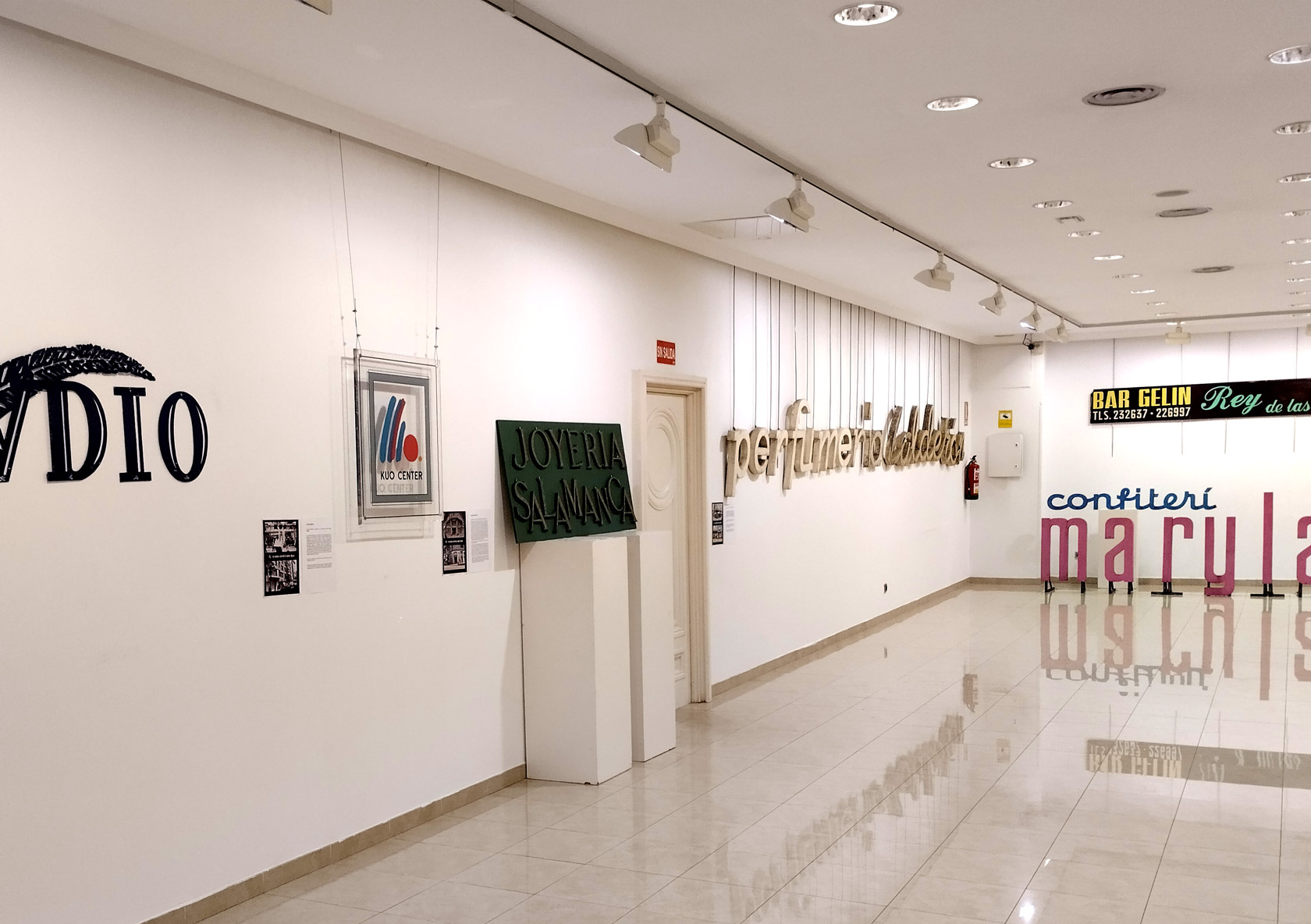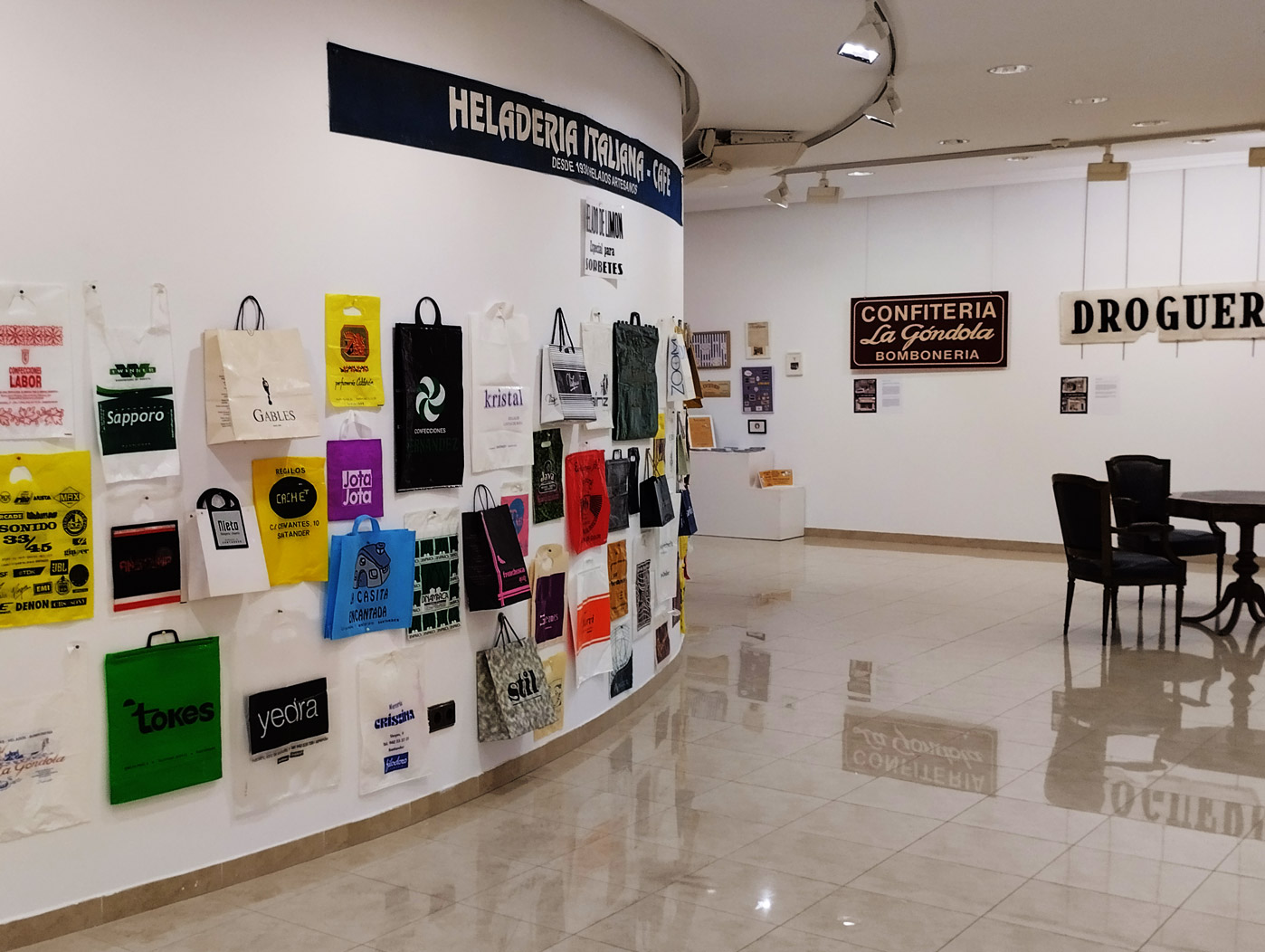
Exposición – He bajao a un recado
“He bajado a un recao. Ahora vuelvo.”
Memoria de lo cotidiano.
Lo cotidiano se hace único en un mundo cada vez más globalizado. Esas letras, grandes, pequeñas, extrovertidas, serias, finas, gordas, con serifa, sin serifa, sencillas, complejas, de plástico, de metal, de madera, pintadas, hechas a mano, a máquina, pensadas, improvisadas, chillonas, sobrias. Esas letras que forman parte de un todo y de una nada, son parte de nuestra memoria más reciente. Estas letras guardan lo que una vez fuimos.
El Patrimonio Gráfico es nuestra identidad local, forma parte de nuestro acervo y sólo conservando y protegiendo los rótulos comerciales, podemos conservar parte de nuestra esencia de comunidad y barrio.
Guardar un pedazo de la historia de la calle. Guardar un pedazo de nuestra memoria colectiva.
Bajo esta premisa se hace esta muestra en el Casino del Sardinero. A través de una docena de rótulos y otros objetos gráficos comerciales, que se han rescatado in situ del contenedor y a pie de obra, y se han donado en otros casos, se invita al visitante a reflexionar sobre los cambios y procesos que se están produciendo en nuestra ciudad. Comercios de toda la vida son sustituidos muchas veces por grandes cadenas y por tanto se pierde una seña de identidad y memoria local.
La labor que se está haciendo desde Santatipo, es rescatar, recoger y preservar este patrimonio gráfico como un patrimonio material e inmaterial de nuestra región, en un mundo cada vez más globalizado y estandarizado. La identidad local pasa desde un bar de barrio hasta una perfumería centenaria. La tipografía y el diseño juegan una gran labor en este aspecto creando y sumando a nuestro imaginario colectivo, pero hay otra parte que es la humana y social: La del barrio.
Los rótulos son elementos cotidianos que están ahí y pasan desapercibidos en nuestra vorágine.